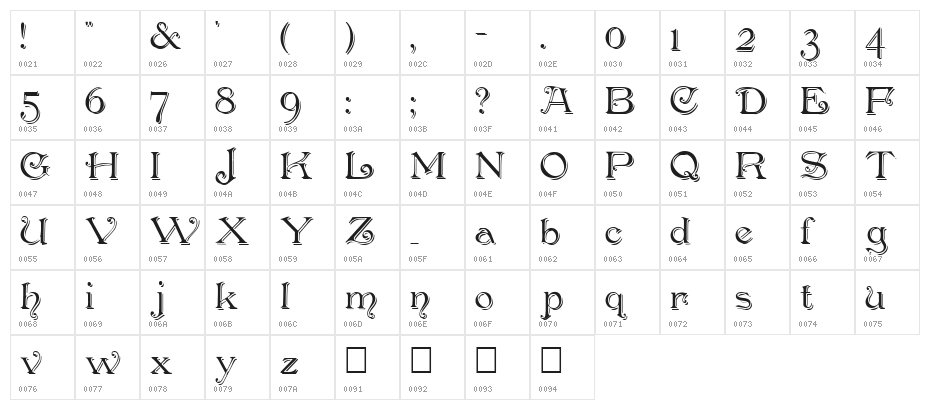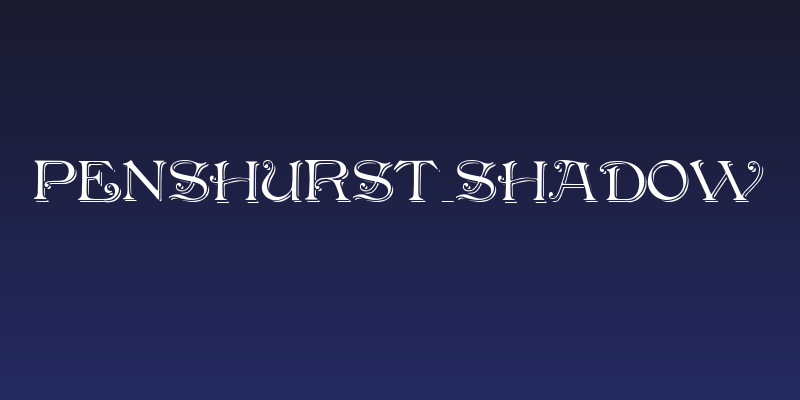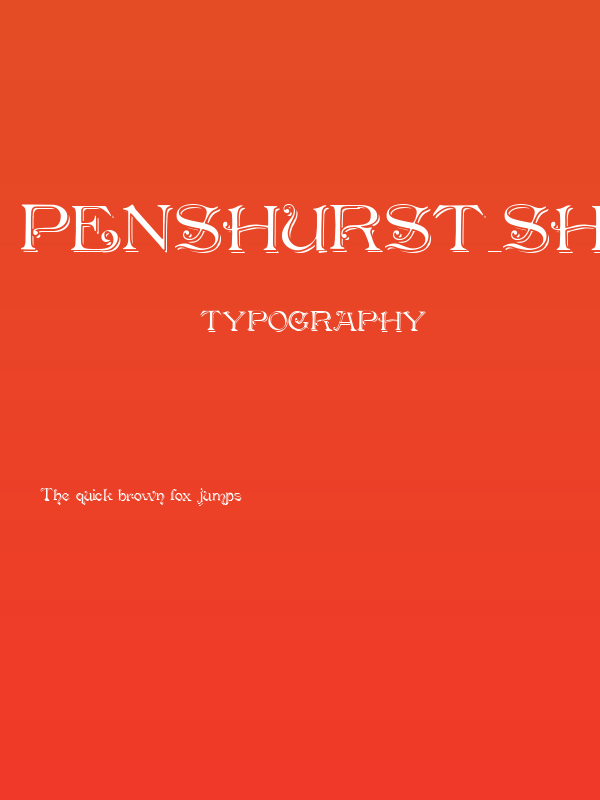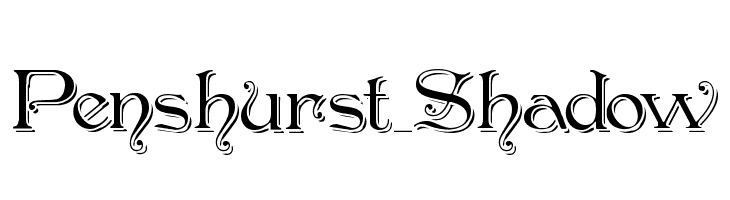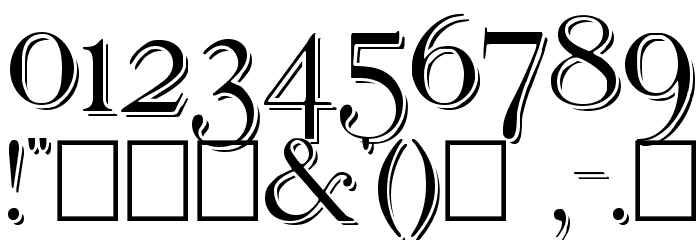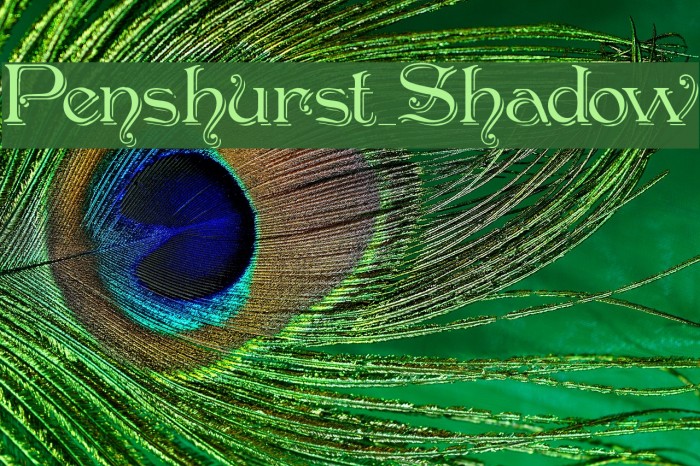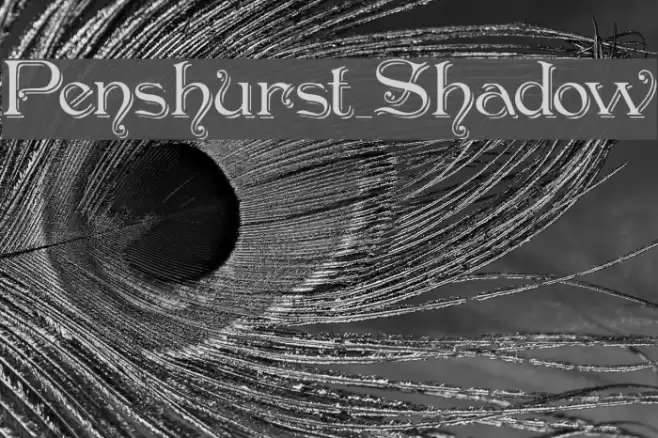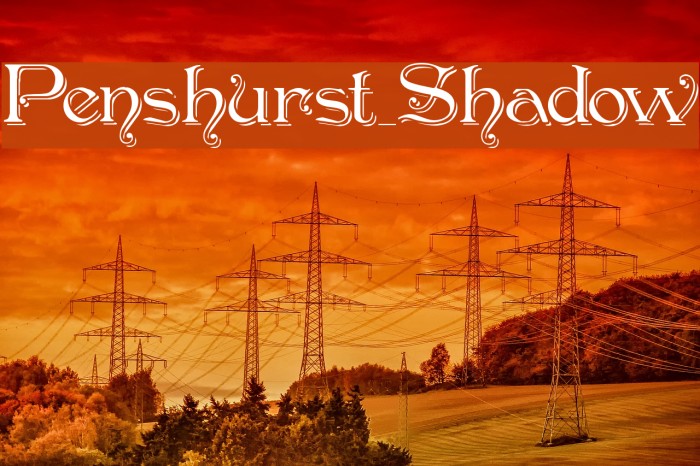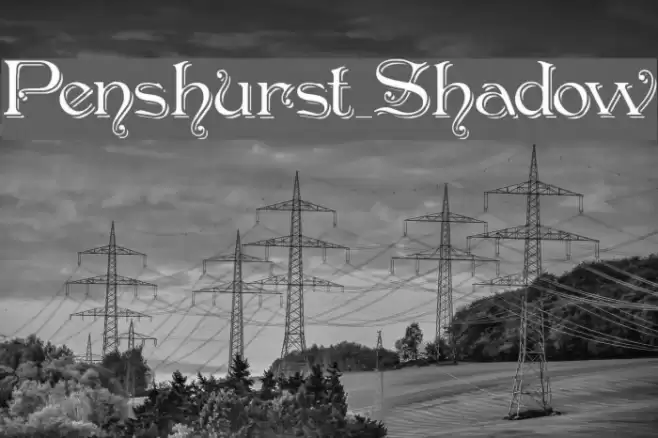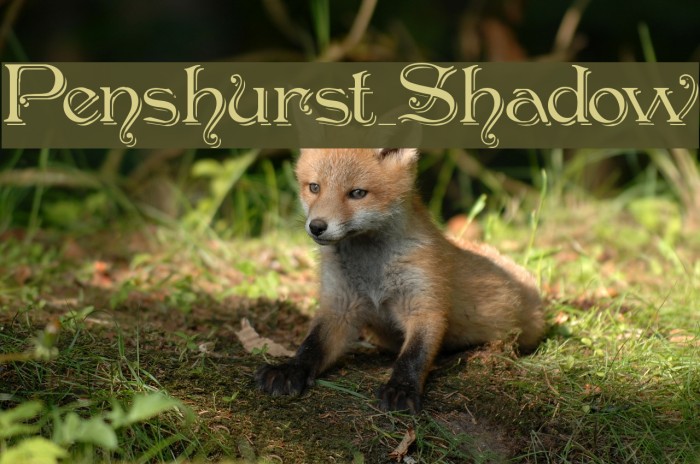
Penshurst_Shadow Font
| Estilo general | Vintage |
| Proyectos propuestos | Ideal for wedding invitations, vintage-themed posters, book covers, and branding that requires a classic and elegant touch. |